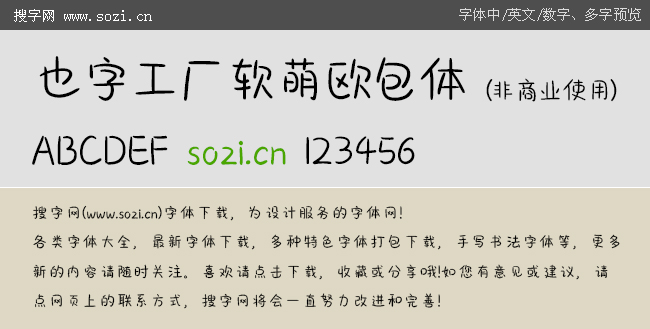
也字工廠軟萌歐包體
搜字網(wǎng)給大家提供一款也字工廠軟萌歐包體(非商業(yè)使用)中文字體下載,也字工廠軟萌歐包體是一款略帶卡通風(fēng)格的手寫字體,字體書寫自然流暢,又帶有一點趣味性,具有很好的視覺效果。適合應(yīng)用于兒童繪本、兒童海報、網(wǎng)頁設(shè)計等應(yīng)用(此字體為個人非商用版,商用可以聯(lián)系:官方網(wǎng)址:https://yefont.com/home,聯(lián)系方式:13798980448)。